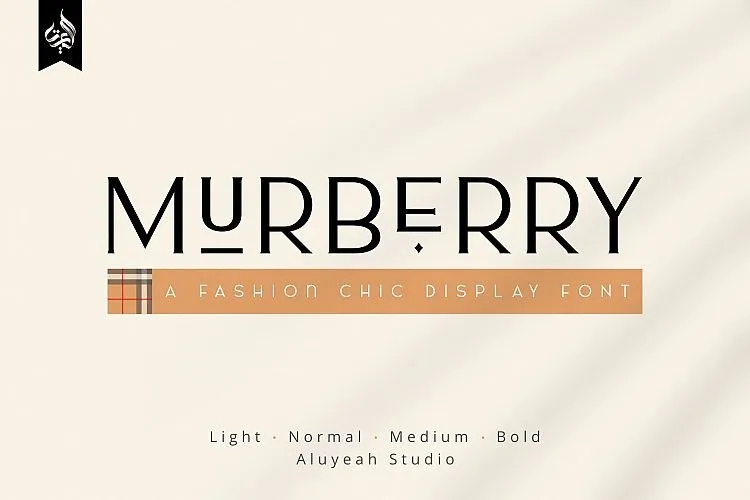
AL Murberry Display Font – Download Grátis
Esta é uma fonte display chamada AL Murberry Display Font. Ela traz um toque sofisticado ao seu design, com linhas elegantes e estilizadas que garantirão que sua apresentação ou logomarca se destaque ainda mais. Desenvolvida pelo Aluyeah Studio, esta fonte é uma escolha perfeita para marcas de moda, resorts, cosméticos, convites, casamentos, embalagens, revistas, boutique, redes sociais, restaurantes, spas, cartões de felicitações e outros materiais. Ela foi cuidadosamente desenvolvida inspirada em um dos principais marcos da moda no mundo. Ao usar essa fonte para sua marca de moda, seu resort ou sua loja de cosméticos, você criará uma aparência luxuosa e elegante que chamará a atenção dos olhos de seus consumidores. O AL Murberry Display Font é uma fonte serif moderna com muitas alternativas para cada caracter. As alternativas adicionam mais opções ao seu design, tornando-o ainda mais personalizável e permitindo-lhe expressar sua marca de maneira única. Este tipo foi projetado para fornecer um aspecto sofisticado e elegante em qualquer aplicação gráfica que você escolha usar, garantido assim uma presença visível e estilosa no meio das redes sociais ou em revistas de moda. Sem dúvidas, essa fonte é perfeita para quem busca dar um toque único à sua marca, seja ela em cartões de felicitações, cabeçalhos, sublinhados do título ou qualquer outro tipo de mídia onde uma boa apresentação faz toda a diferença.